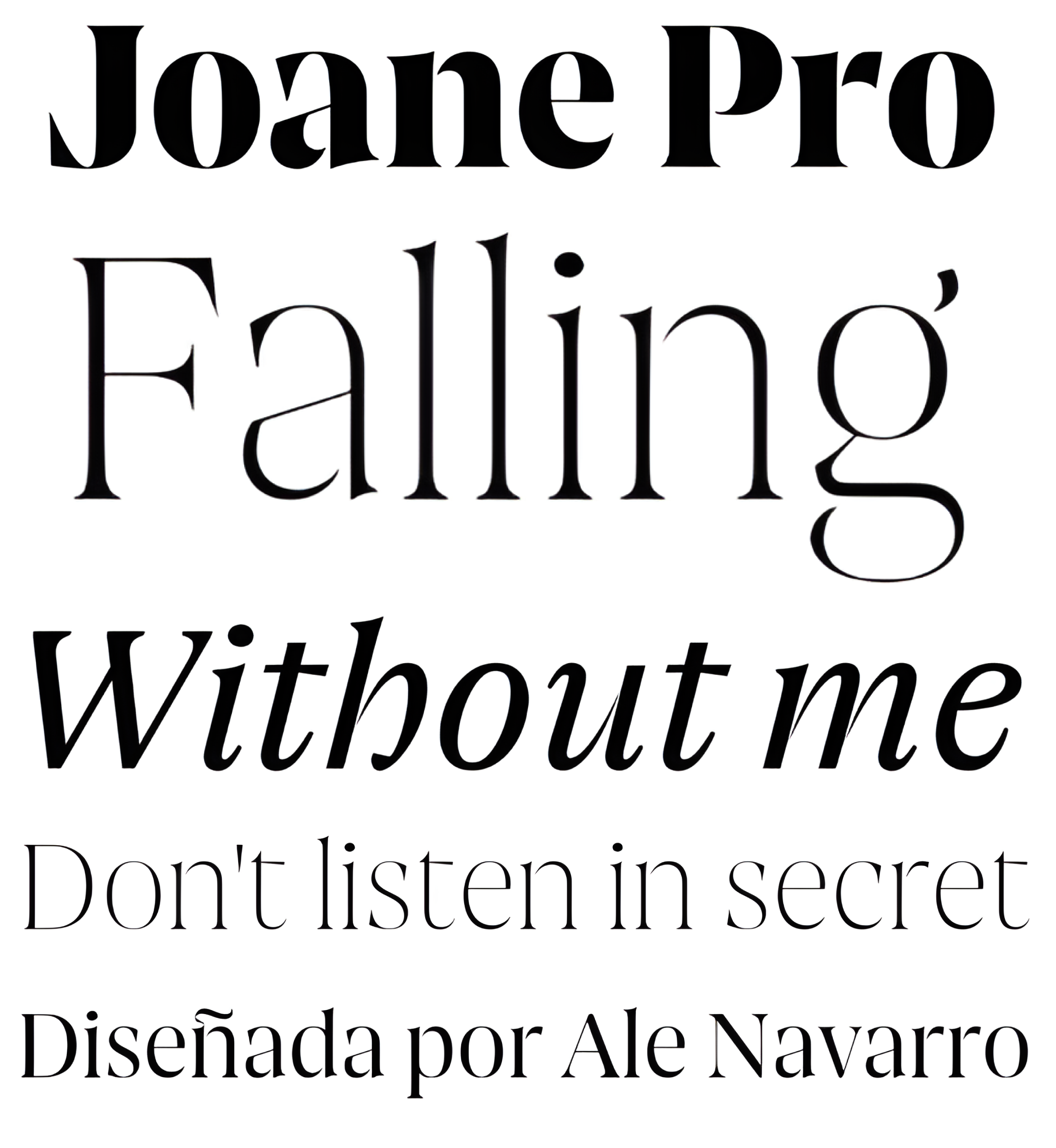
| Año | 2023 |
| Créditos | Ale Navarro |
| Descripción | Joane Pro es un nuevo tipo de letra basado en Joane (2018). Este proyecto tiene sus raíces en la tipografía francesa del siglo XVI, los modelos holandeses del siglo XVII y la tipografía inglesa del siglo XVIII. El resultado es un tipo de letra de alto contraste con rasgos nítidos que proporciona una textura orgánica. Joane Pro es un tipo de letra contemporáneo con 79 estilos que funcionan en pantalla y en tamaños pequeños. |
| Estilos | 79 |
| Fundidora | W Type Foundry |